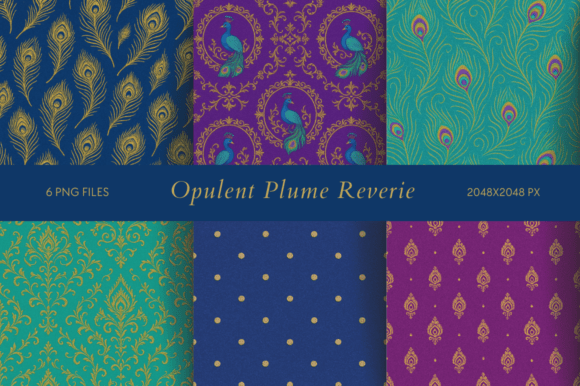
Opulent Plume Reverie
Если вы ищете высококачественные ресурсы, такие как Opulent Plume Reverie, этот премиум-пакет — фантастический выбор для ваших творческих проектов.
Создаете ли вы продукты POD (печать по требованию), свадебные приглашения или графику для социальных сетей, Opulent Plume Reverie станет идеальным выбором.